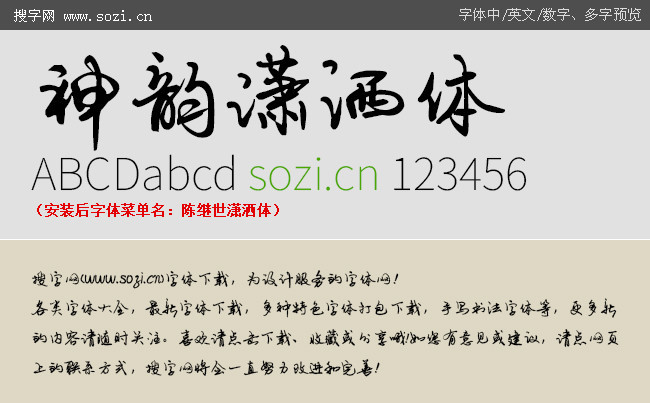
神韻瀟灑體
搜字網(wǎng)給大家提供一款漢神韻瀟灑體中文字體下載,神韻瀟灑體是一款非常陽剛的字體,字體瀟灑自如,非常飄逸而不失風(fēng)度,適合應(yīng)用于平面海報(bào)設(shè)計(jì)、包裝設(shè)計(jì)等廣告應(yīng)用。(本字體為個(gè)人非商用版,如需要商用請(qǐng)聯(lián)系作者購買版權(quán))